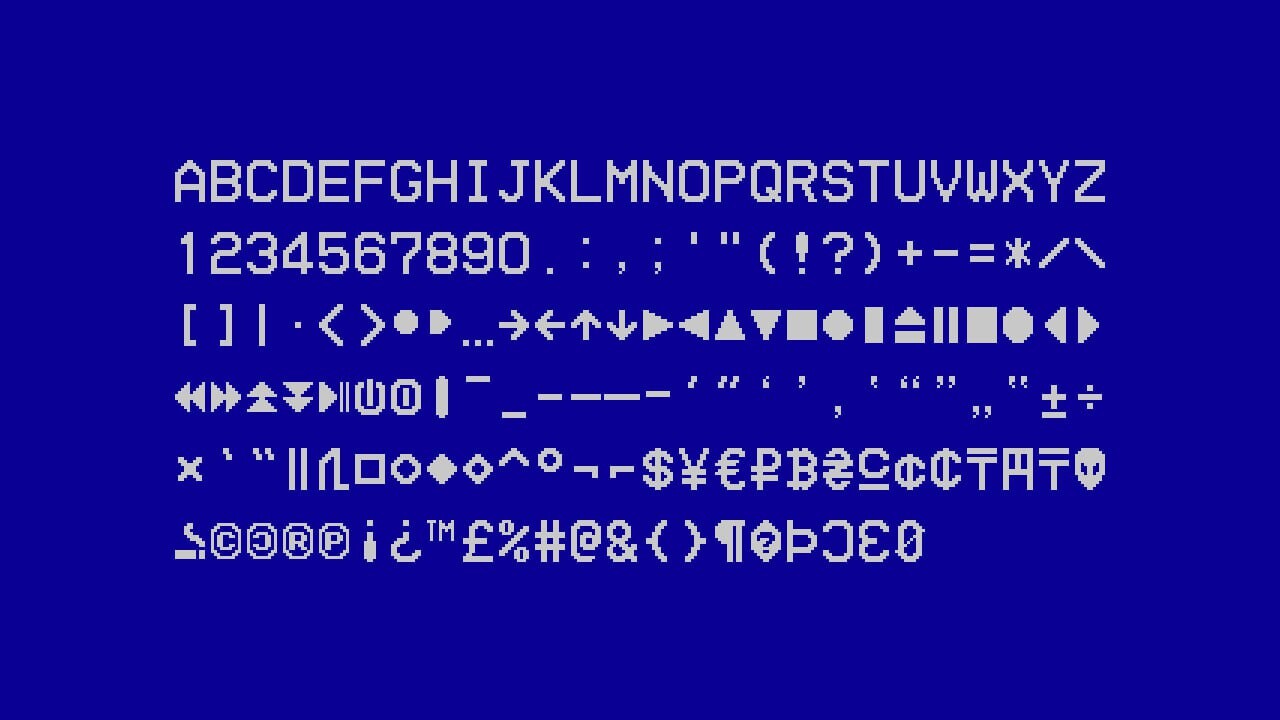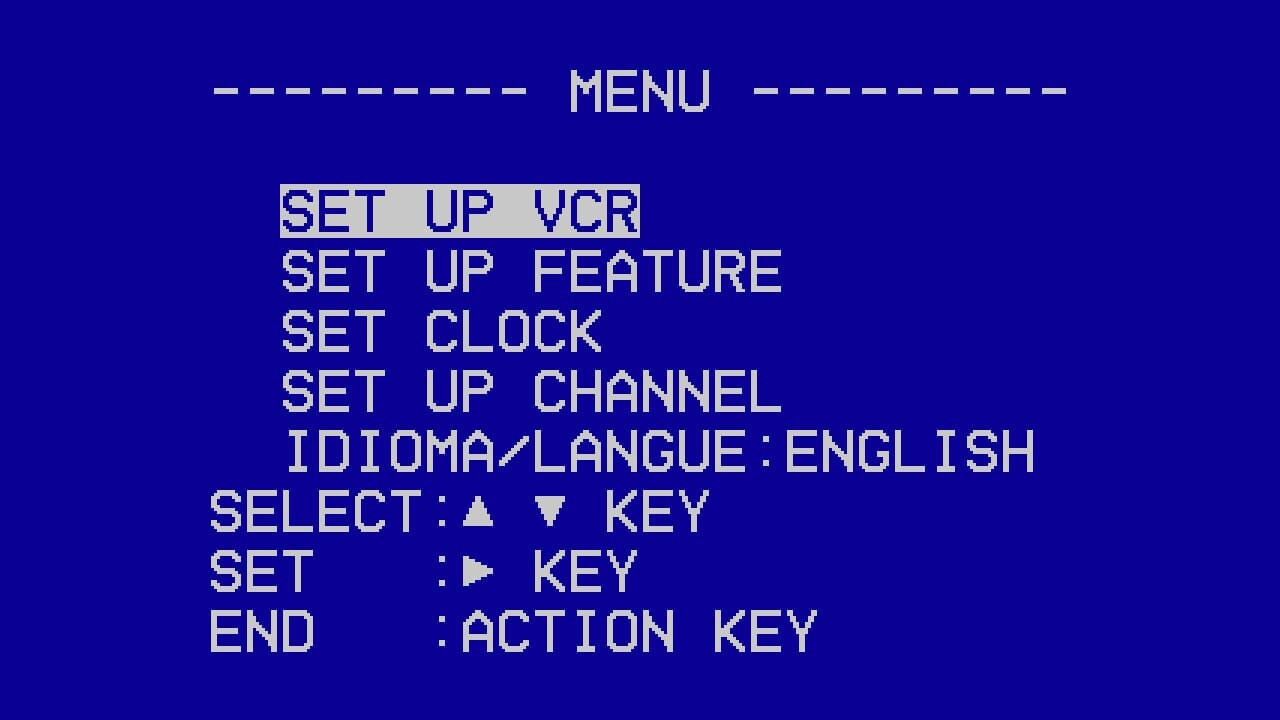
Ретро шрифт в пиксельной стилистике, вдохновлённый экранными шрифтами первых видеокассет. Предлагает два варианта начертания: стандартное (как на превью) и Bold. Шрифт поддерживает только латиницу, цифры и специальные символы. Доступен для использования абсолютно бесплатно.